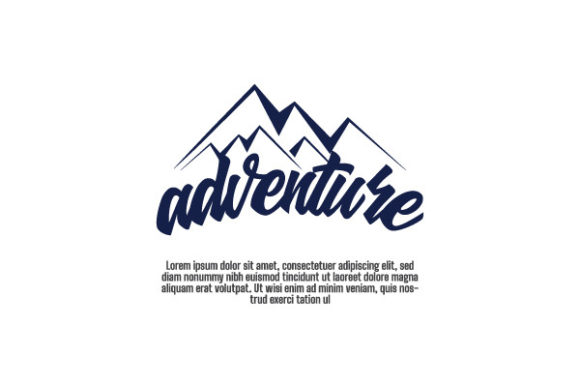
Mountain Adventure Script Logotype
การค้นหาองค์ประกอบการออกแบบที่เหมาะสมอาจเป็นเรื่องท้าทาย แต่ Mountain Adventure Script Logotype นำเสนอคอลเลกชันที่โดดเด่นซึ่งช่วยยกระดับงานของคุณได้ทันที
สร้างขึ้นอย่างแม่นยำ Mountain Adventure Script Logotype ให้เวกเตอร์ที่สะอาด พิมพ์ตัวอักษรที่ราบรื่น และใบอนุญาตเชิงพาณิชย์เพื่อความสบายใจ